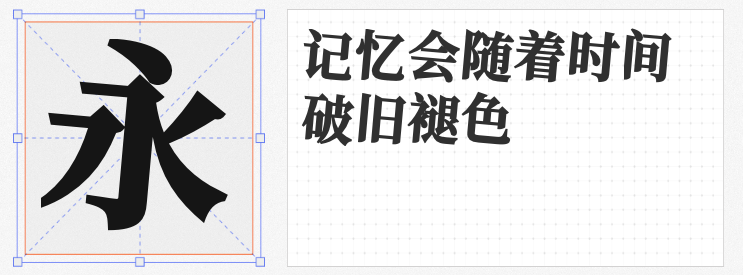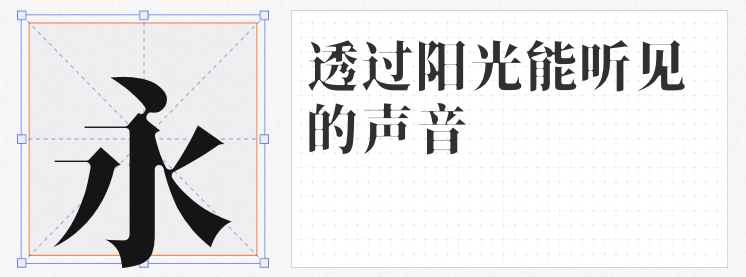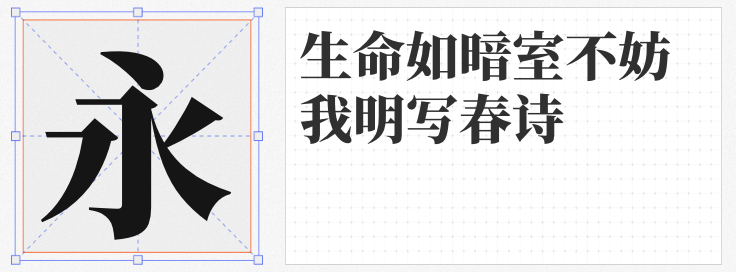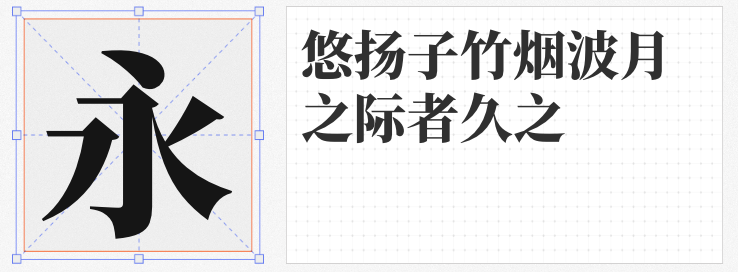
宋体作为汉字文化的经典载体,其端庄典雅的韵味与现代设计的融合,始终是设计师探索的课题。以下四款免费商用宋体字体,以独特的设计语言打破传统框架,为广告、包装、出版及数字媒体等领域注入新鲜活力。
1. 香萃潮汐宋 W40
这款字体以圆角处理为核心,将传统宋体的棱角转化为柔和曲线,搭配横细竖粗的强烈对比,形成清新明快的视觉节奏。其粘连笔画设计如雾气缭绕,既保留了人文雅韵,又暗藏恐怖题材所需的张力——蛛网般的朦胧感与藕断丝连的细节,让同一字体在书刊印刷中展现诗意,在悬疑设计中释放压迫感,堪称“多面手”。
2. 昭源宋体 Heavy
作为昭源字体家族的宋体分支,这款字体与黑体版本形成完美互补。其设计语言紧扣现代审美,收字量庞大且字重层级丰富,从屏幕显示到印刷出版均能保持清晰锐利。开源特性更使其成为团队协作与跨平台设计的理想选择,兼顾效率与品质。
3. 尚古明体 Heavy
基于思源系列深度优化的尚古明体,突破单一语言界限,实现中日韩文字的统一呈现。字体家族涵盖黑体、圆体及简繁转换版本,满足多语言排版需求。其宋体版本保留传统书法的飞白意境,同时通过结构调整提升屏幕阅读舒适度,适合文化类项目与国际化设计场景。
4. 新愚公和谐宋-H
针对思源宋体横细竖粗的经典比例,新愚公和谐宋通过整体加粗处理,消解了原字体在特定场景下的头重脚轻感。这种“微调哲学”既延续了思源系列的开放基因,又以更均衡的笔画分布适配标题设计与长文本排版,成为免费字体中“低调的实力派”。
四款字体各具锋芒,从实验性设计到功能优化,从文化表达到技术兼容,为设计师提供免费且高质量的宋体解决方案。